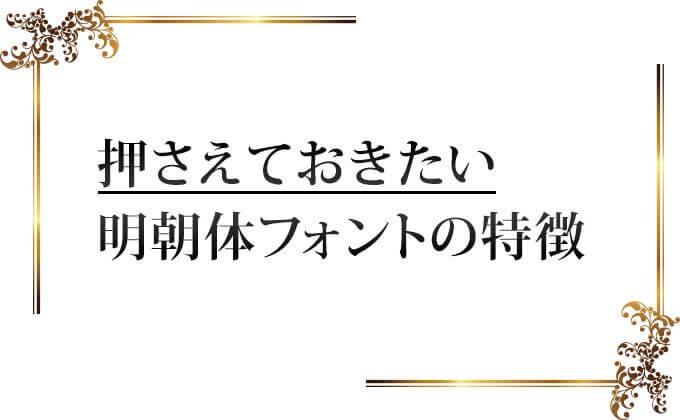
デザインに適したフォント、毎回選択するのですが、
書体の特徴を理解するとグッと選びやすくなるのではと思います。
そこで、今回の主役は「明朝体」です。
押さえておきたい基本から、フォントの種類の紹介をします。
明朝体の基本
日本語の文字は、明朝体とゴシック体に分けることができます。今回フォーカスする明朝体は、横線に対して縦線が太いです。更に、横線の右端、曲り角の右肩に三角形の山(ウロコ)があります。
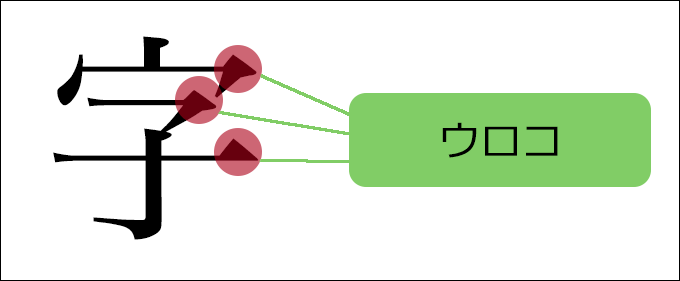
このウロコがあることで、文字が小さくなり横線が薄くなっても、横線があると認識できます。
フォントごとの違い
以下、3種を紹介します。全て同じフォントサイズ(43px)で作成しています。
A-OTF リュウミン
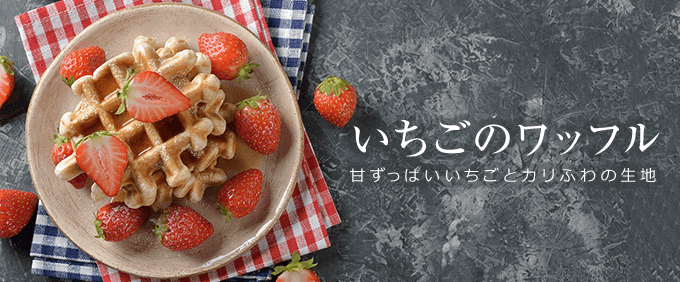
彫刻刀の冴えを文字に活かしたフォントです。現在では、DTPの基本書体として幅広く、本文組みから見出しまで使用されています。
ヒラギノ明朝
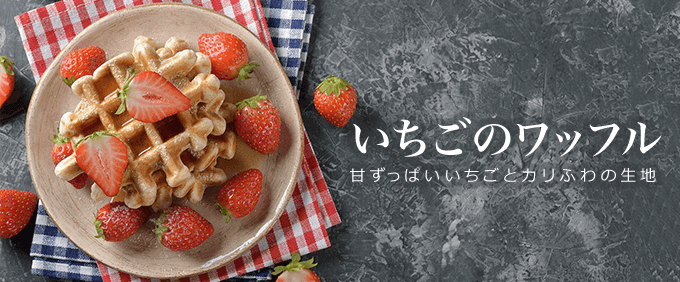
ヒラギノ明朝は、本文用書体として開発されました。そのため可読性が高く、長い文章に適したフォントと言えます。ただし、macにのみ標準搭載されているようです。
小塚明朝pro
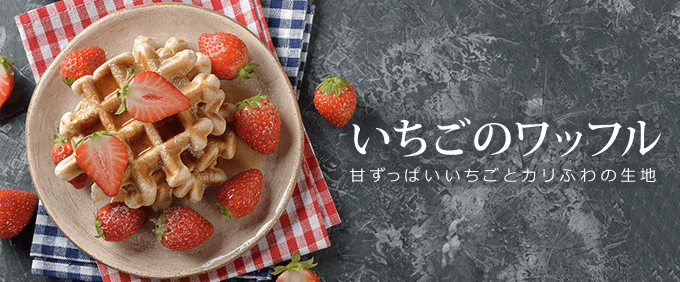
上の2つに比べ、曲線に丸みがありふところが広いですね。
これは、時代の要請により変化した結果で、スマホやPCでの文字の視認性をあげているようです。
webサイトで明朝体を使う際、
気をつけるべきこと
現在Androidは明朝体が搭載されていません。
明朝体を使ったデザインをしたいときは、webフォントを利用する方法があり、有名なのはGoogleフォントです。
奥が深い書体
日本語に明朝体/ゴシック体があるように、欧文フォントにはサンセリフ体とセリフ体があります。
デザインによってそれらの使いどころを見極められるようになれれば、
目指したい形に少しでも近づくのではと思います。